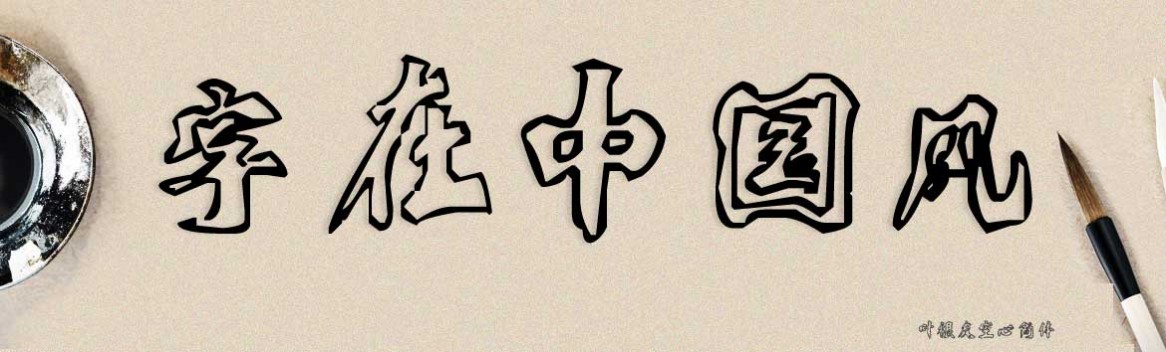
叶根友空心简体
字体作者:叶根友
创作年代:2007年7月1日
字体字数:6763个中文汉字以及其他英文字母和阿拉伯数字
字体介绍
叶根友空心简体是叶根友先生创作字体以来第一款字体,现在看来非常的有意义,这个字体作品虽然回过头去看看,不是非常的满意,但是却是开创叶根友字体系列的一个奠基石,所以对这个空心简体感情很深,叶根友空心简体字体是在2005年就打算把空心字做成字库的想法,后来经过两年来的书写创作,终于完稿,由于第一次写字库字体,没有什么经验,以致与有些笔画结构不是很好,这样叶根友空心简体是由邳州书法家禚效锋老师制作的,在这里对他的辛勤付出表示感谢!